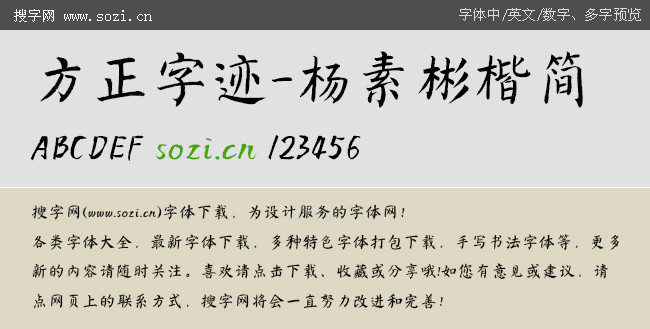
方正字跡-楊素彬楷簡(jiǎn)
搜字網(wǎng)提供一款方正字跡-楊素彬楷簡(jiǎn)中文字體下載,此套字庫(kù),源于唐顏真卿顏勤禮碑,書(shū)寫(xiě)時(shí)進(jìn)行了再創(chuàng)作,且保留了顏體楷書(shū)的基本特征。結(jié)構(gòu)上端莊雍容寬博大氣,而書(shū)寫(xiě)時(shí)加快了速度,增添了靈活性。整體更具時(shí)代感。
- 風(fēng)格類(lèi)別: 手寫(xiě)書(shū)法體